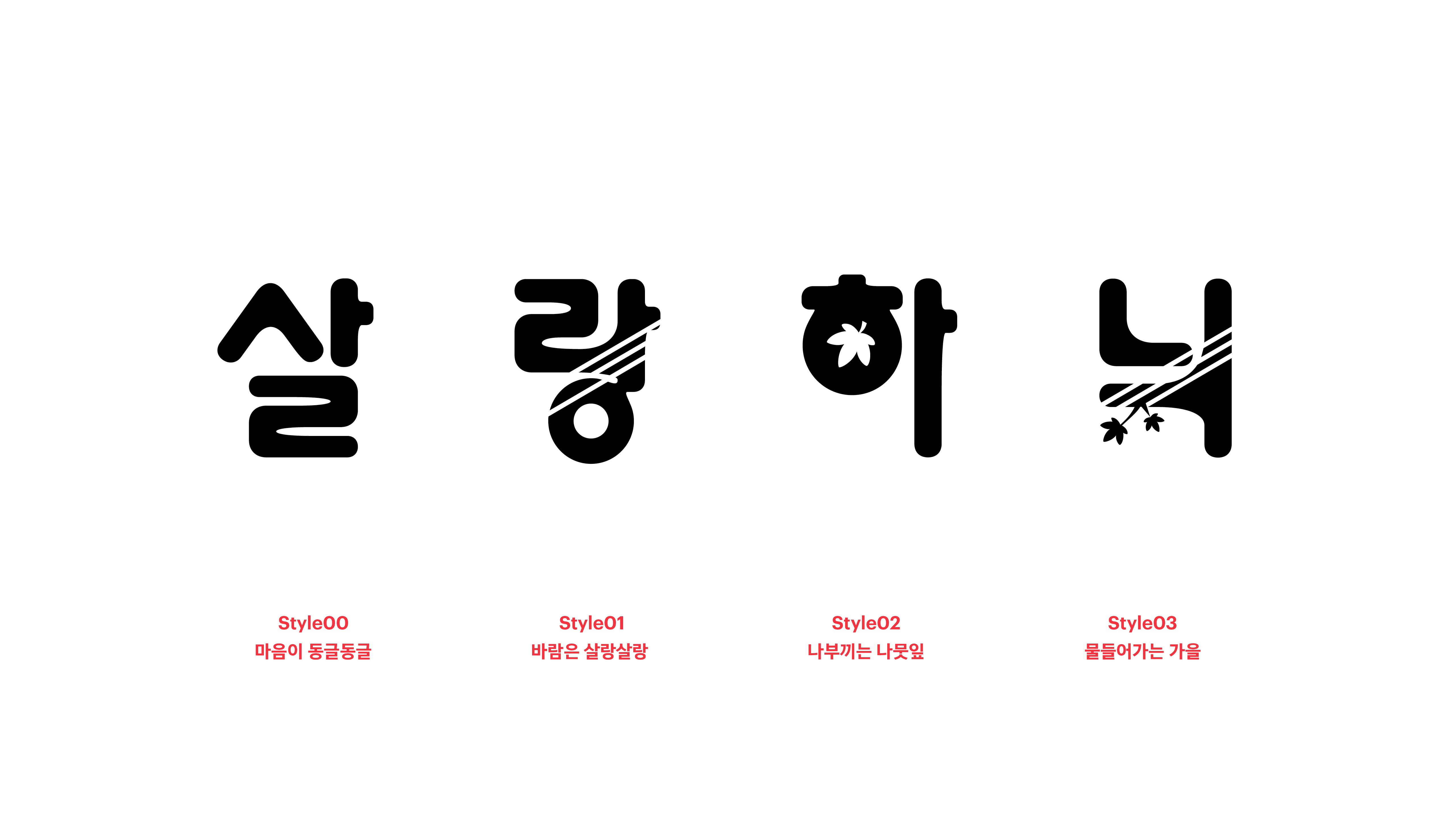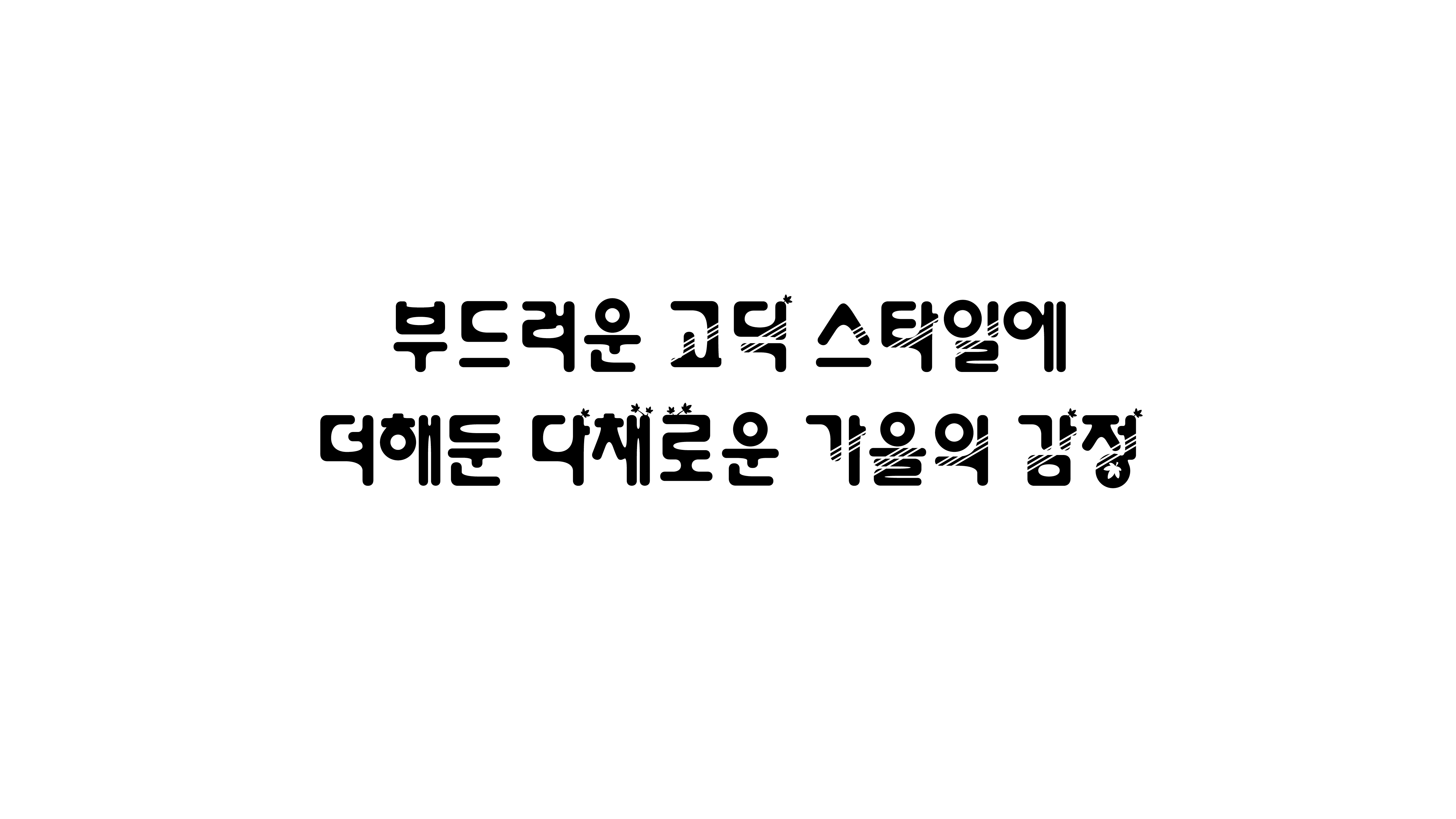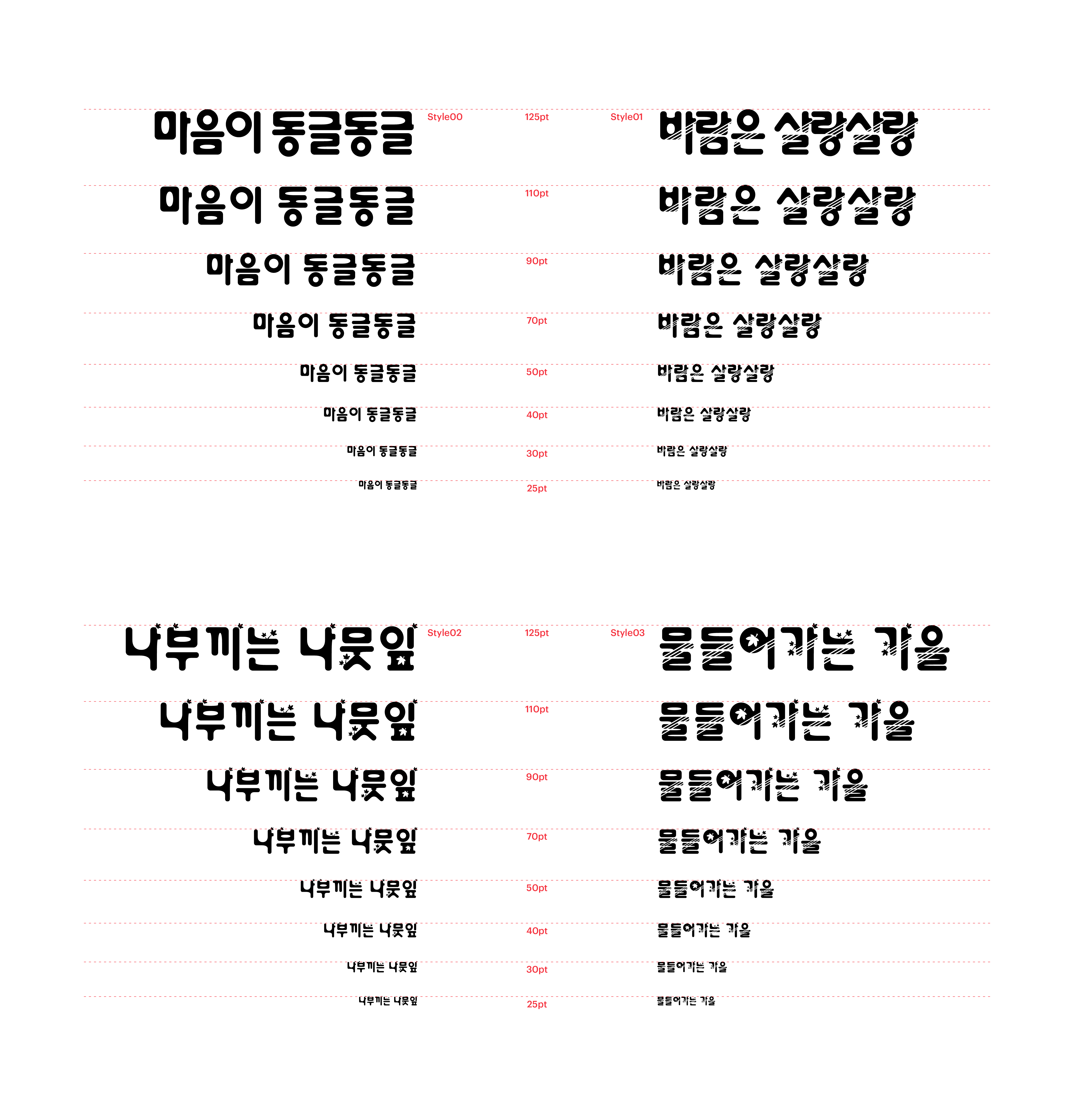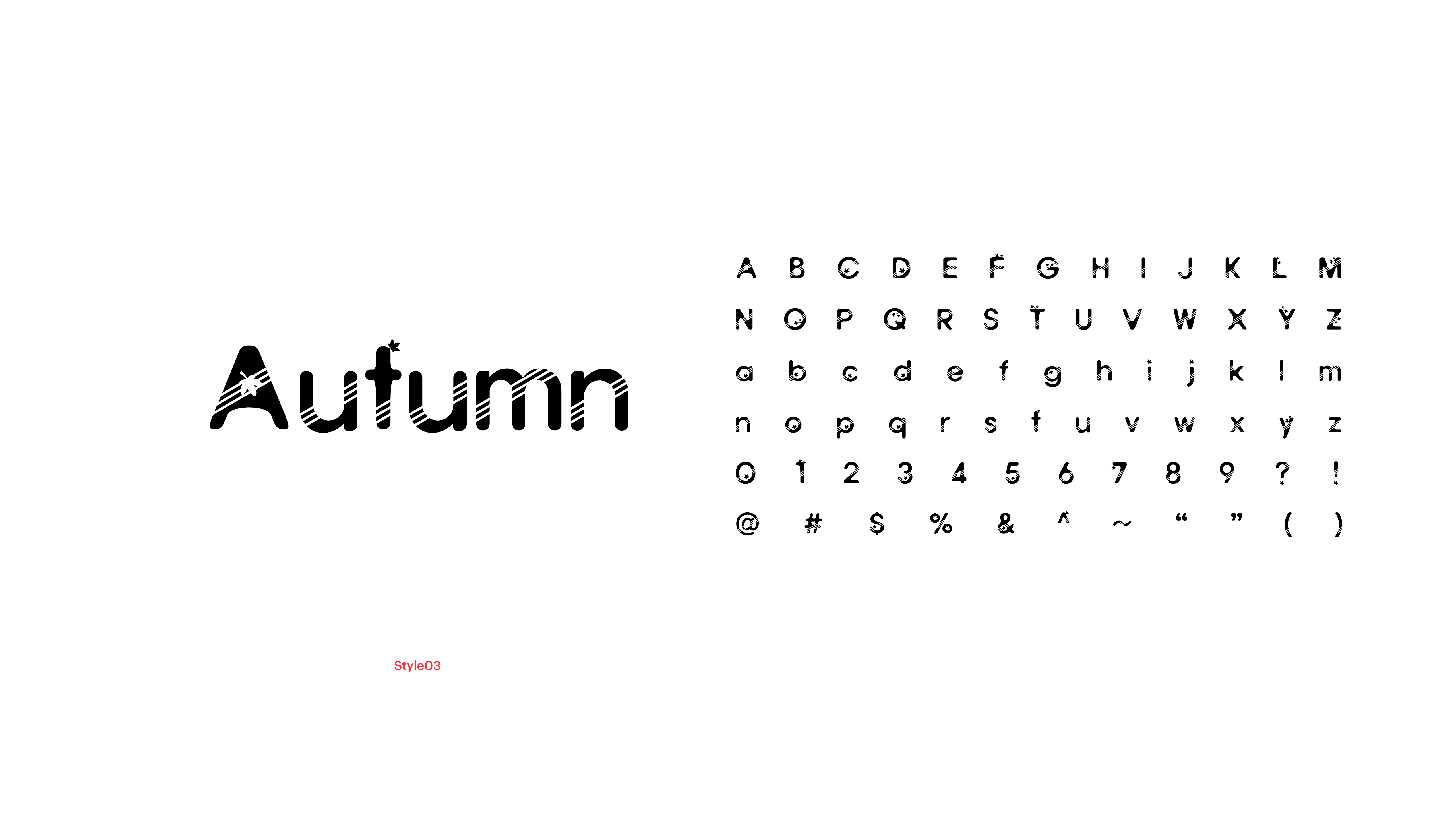
가을바람 불기 시작하면 모났던 마음이 둥글어집니다. 하지만 요즘 가을은 너무 짧죠? 이 아름다운 계절을 붙잡아두고 싶은 마음을 담아 살랑하늬 네 종을 개발해보았습니다. 부드러운 고딕 스타일의 폰트에 불어오는 바람, 나부끼는 나뭇잎, 물들어가는 가을의 빛을 연출할 수 있는 효과를 포함해두었어요. 그러니 짧은 가을을 미리 아쉬워하지 말고, 가을의 정서를 가장 가을답게 표현해보는 거예요.
Yoon 살랑하늬